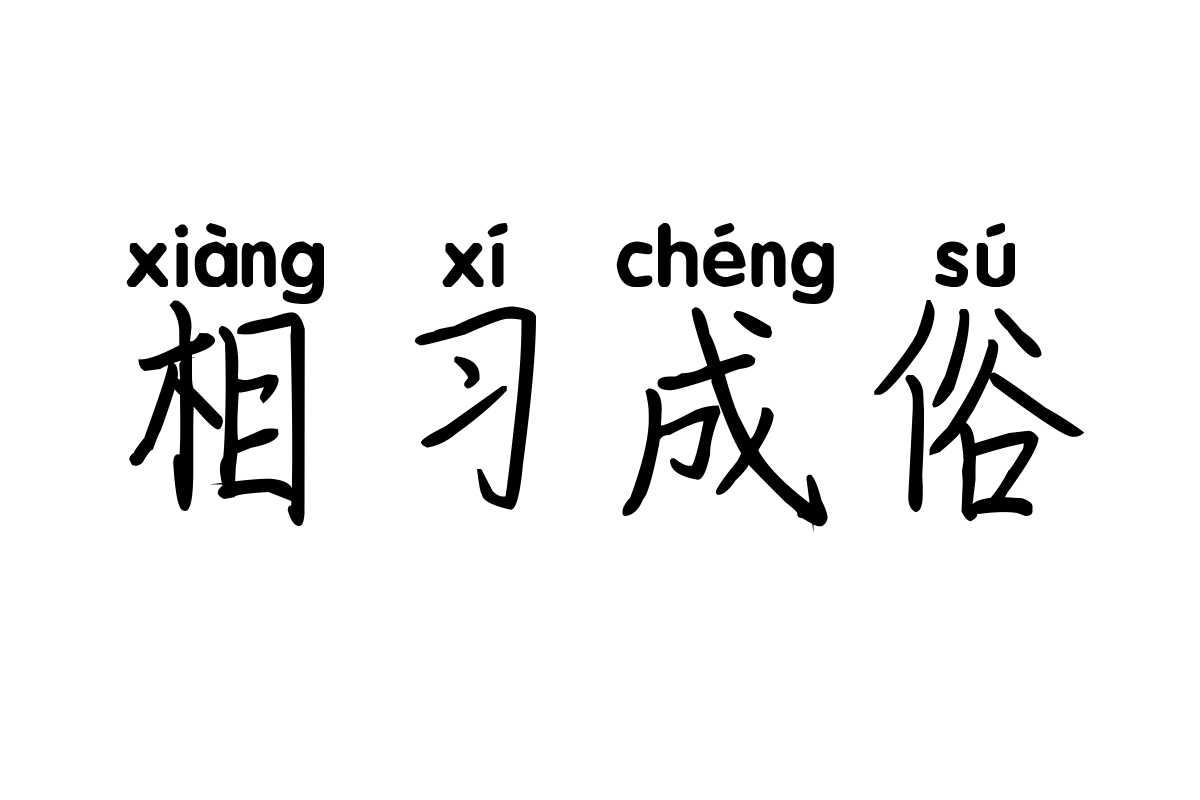
米开第一封情书拼音体是一款基于汉字的字体,它以汉字为基本元素,通过拼音的方式将汉字进行组合。这种字体的特点是简洁明了,易于阅读,同时也具有一定的艺术感。
米开第一封情书拼音体的特点如下:
1. 字体结构:字体由多个汉字组成,每个汉字之间用空格隔开。字体的整体形状类似于一封情书的形状,因此得名“情书体”。
2. 字体风格:字体的风格简约,线条流畅,给人一种清新的感觉。同时,由于使用了拼音的方式,使得字体具有一种独特的艺术感。
3. 适用场景:这种字体适用于需要表达情感、爱情主题的场合,如诗歌、歌词、广告等。
4. 使用注意事项:由于这种字体是基于汉字的拼音方式构建的,因此在使用时需要注意汉字的读音和拼写,以免出现误解或混淆。